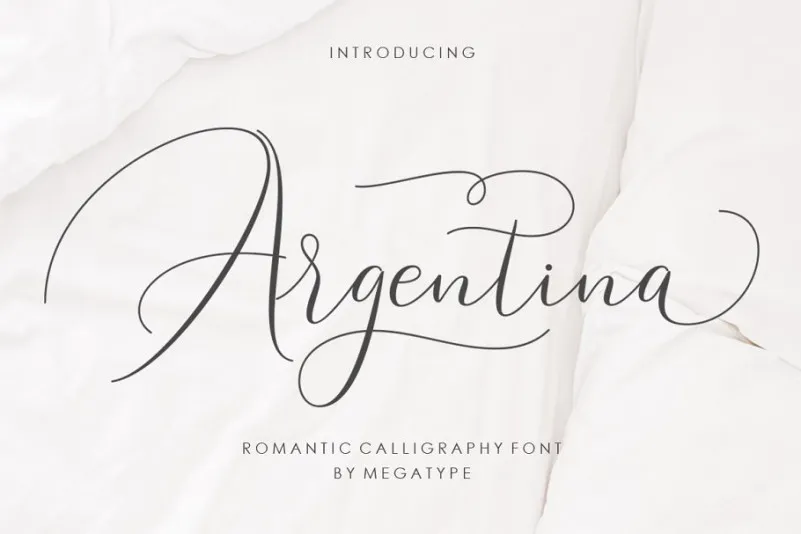
Argentina Script Font – Download Grátis
A Argentina Script Font é uma linda tipografia que combina elegância com delicadeza, perfeita para quem busca um toque romântico e sofisticado em seus projetos digitais. Especialmente indicada para gráficos de alta qualidade, como cartazes, selos e embalagens personalizadas, esta fonte vem equipada com linhas suaves e uma base de deslocamento variável que adiciona um toque refinado a qualquer texto. A Argentina Script Font é ideal para criar títulos impactantes, selos criativos para aniversários ou eventos especiais, embalagens de produtos personalizadas e até mesmo materiais promocionais, como cartazes publicitários ou cartões de convite. Seu design elegante e romântico se destaca em qualquer aplicação visual que exige um toque especial de sofisticação. Com a Argentina Script Font na sua coleção de fontes digitais, você pode impressionar seus clientes com um design único e moderno sem precisar recorrer à impressão. Essa fonte premium, criada pelo designer 178-MC, é perfeita para designers gráficos que buscam um acabamento sofisticado em suas criações digitais.